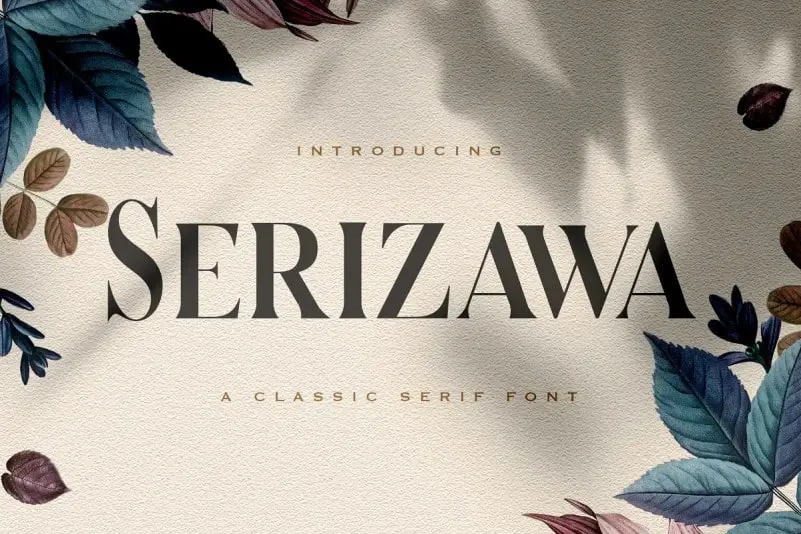
Serizawa Serif é uma fonte serif com alta contraste que exala elegância tanto para projetos vintage quanto para modernos. Desenhada pela StringLabs, a fonte atinge um alto nível de precisão e bom gosto, ideal para qualquer projeto que valorize os detalhes cuidadosamente criados. Com seus traços precisos e contrastes marcantes, Serizawa tem uma característica única capaz de se adaptar facilmente a diversos tipos de projetos. Seja você um amante da arte vintage ou um criativo moderno buscando uma fonte que destaque suas ideias com clareza, Serizawa Serif está aqui para ajudar a tornar seus trabalhos ainda mais chamativos e memoráveis. Adicione-a às suas próximas criações e note como ela as faz brilhar de forma singular.